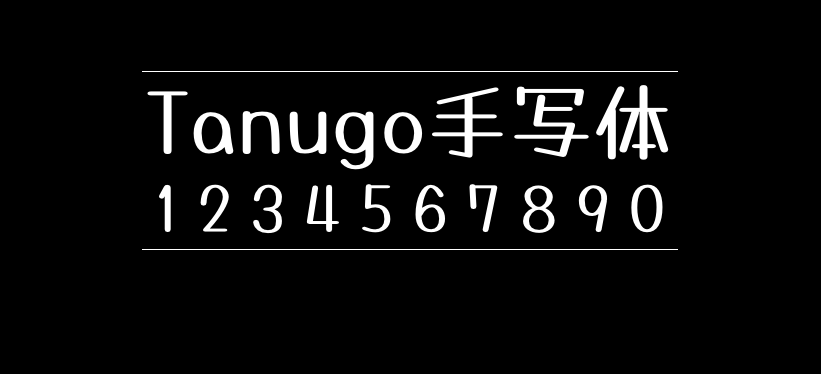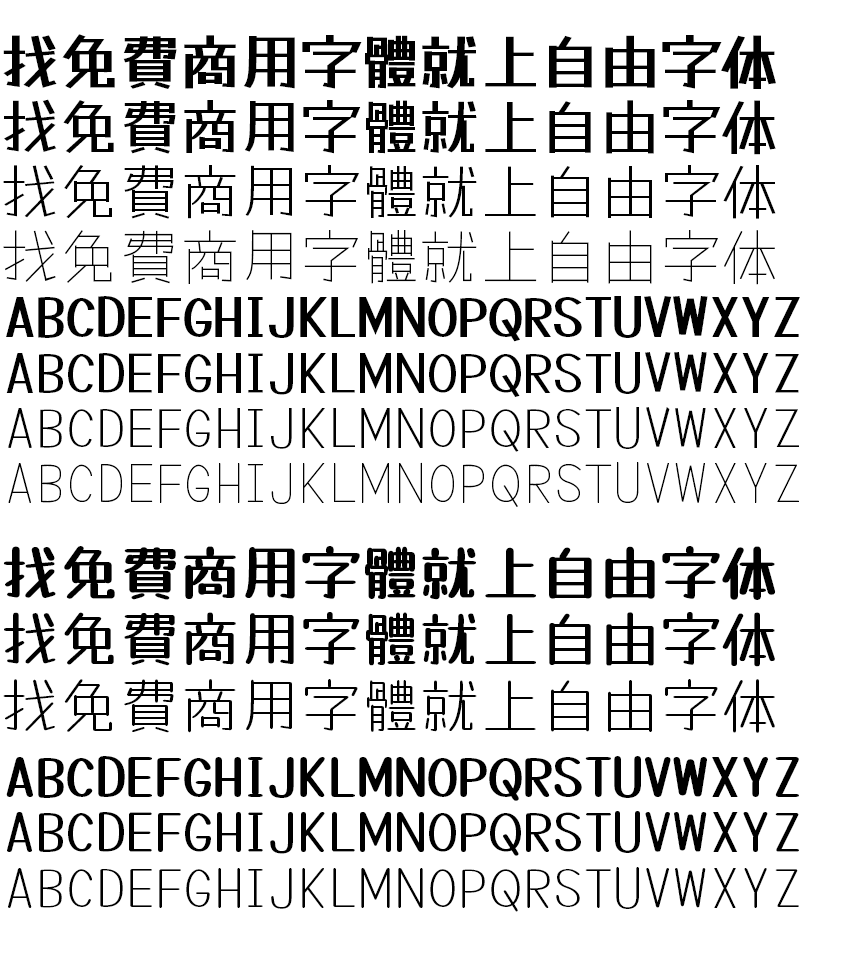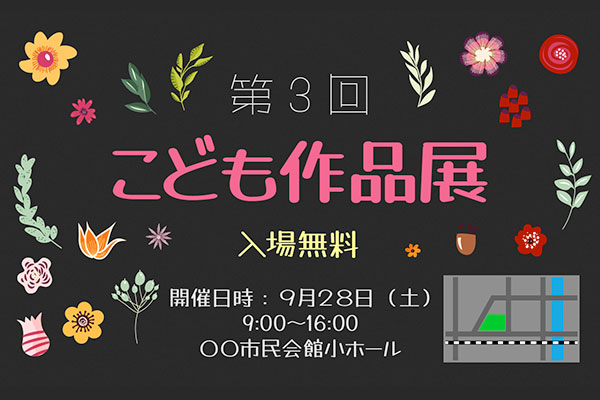
Tanugo手写体
Tanugo手写体(たぬゴ角 Tanugo-S / たぬゴ丸 Tanugo-R)是基于本站之前发布过的“马克笔手绘体”的更新版而制作的字体。Tanugo手写体保留了马克笔手绘体的特征,保持亲切性的同时,更容易使用、容易阅读。这是一款以可爱的类型设计为目标而制作的字体。
Tanugo手写体收录了平假名、片假名、字母数字、符号、到JIS第二水准的汉字以及移动IBM扩展汉字(共计7000字以上),并且扩展为两种样式。字体名中带“角”(S)字的字体样式,是硬边的设计。而字体名中带“丸”(R)字的样式,则边角是圆润的设计。
不仅如此,Tanugo手写体还扩展了字体的字重,其中硬边S版具备ExtraLight、Light、Regular、Bold 4个字重,圆角R版提供了Light、Regular、Bold 3个字重。虽然这款字体是由日本人制作的,但是中文繁体字符还是相对较全的,喜欢的不要错过了!